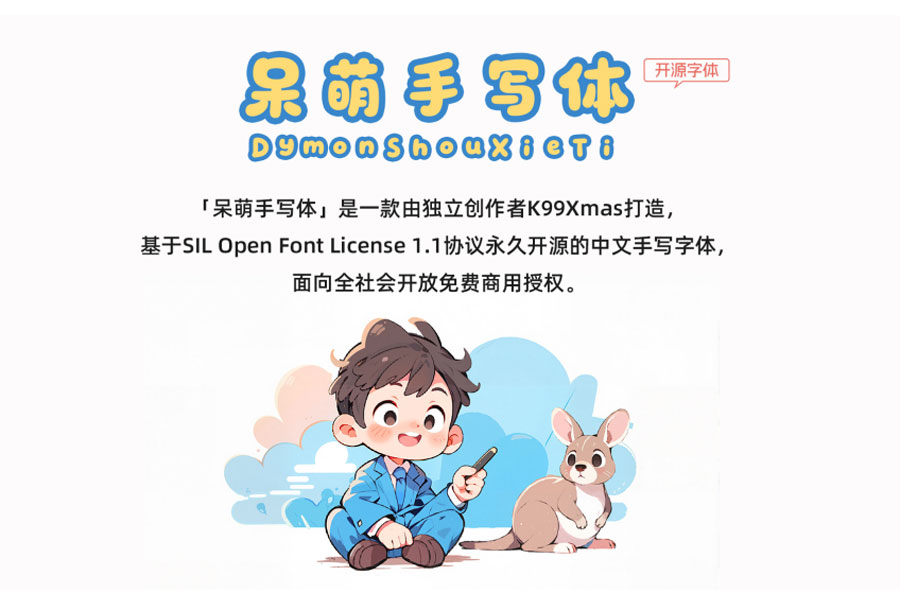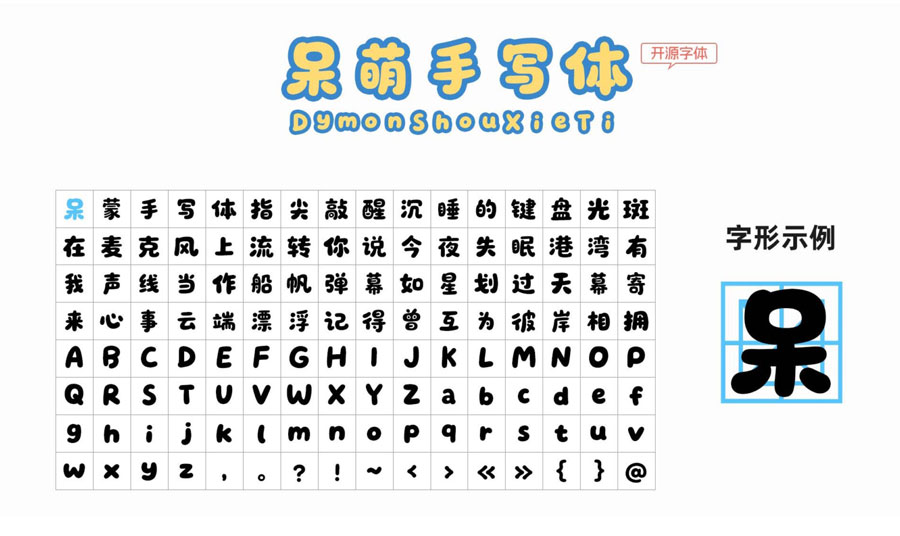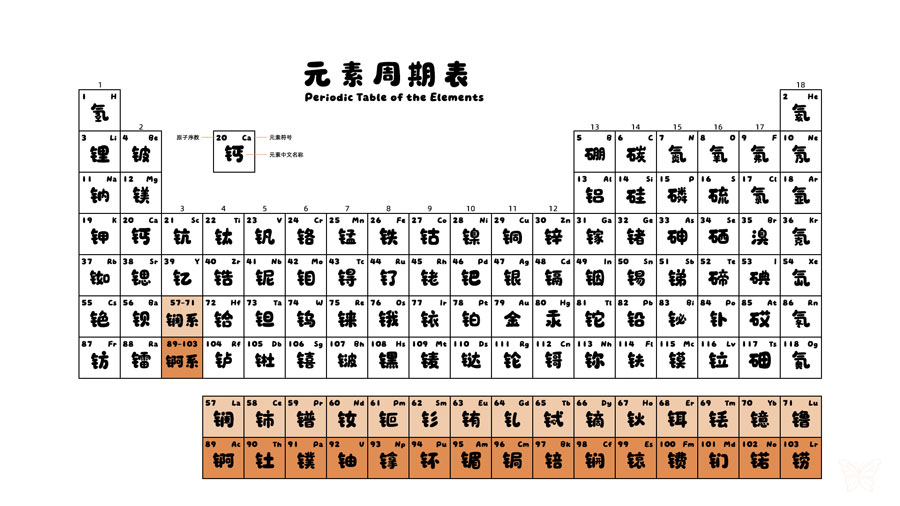
呆萌手写体(DymonShouXieTi)是由B站独立创作者K99Xmas设计、基于SIL Open Font License 1.1协议永久开源的免费商用中文手写字体,于2025年6月1日儿童节正式发布。其最大特点是通过圆润Q弹的笔画结构、适度的墨迹留痕和童趣连笔设计,在保证文字识别度的同时营造治愈系视觉风格,适用于文创设计、儿童教育、新媒体传播等多元场景。
呆萌手写体(DymonShouXieTi)是由 B 站 UP 主 K99Xmas 于 2025 年六一儿童节设计发布的一款免费可商用中文手写字体。
整体字形扁宽,重心居中,笔画粗细一致,均为圆头设计,没有尖锐棱角,线条弧度柔和,有点类似孩童用蜡笔在随手涂鸦,既可爱又很治愈。可以适用于文创设计、儿童教育、新媒体传播等多种场景。
字符扩增:补齐元素周期表相关字符,总字符数增至 7639 个。
字符扩增:补齐 《现代汉语通用字表》,总字符数增至 7625 个。
字符扩增:补齐 GB/T2312 标准字库,总字符数增至 7239 个。
字形优化:优化部分字形结构,提升美观度与一致性。
首发版本:六一儿童节正式发布。
收录基础常用汉字与符号,满足基本设计需求。
确立圆润稚拙、Q 弹可爱的核心手写风格。